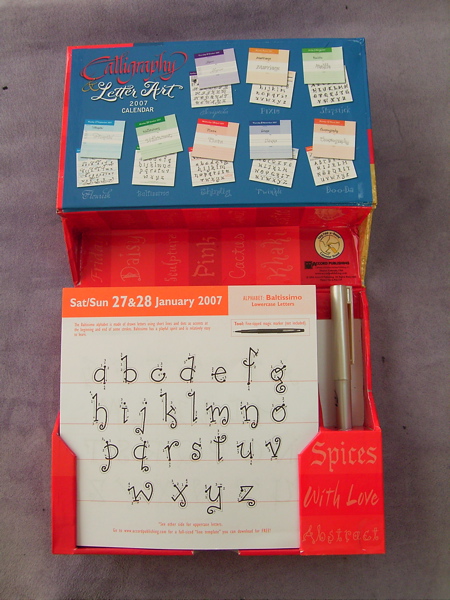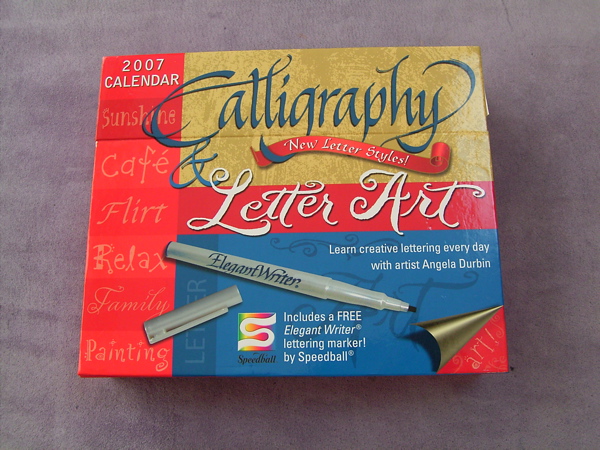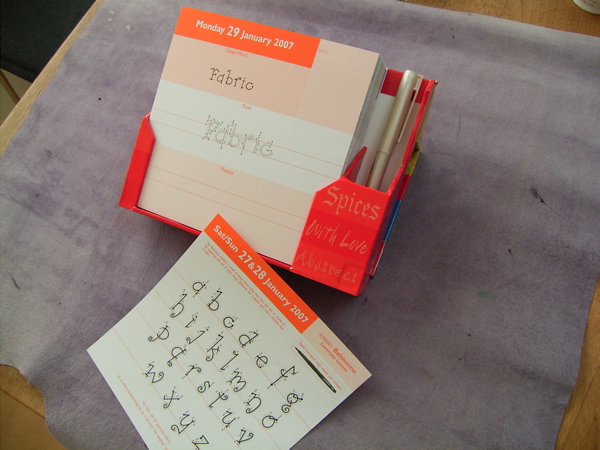
カリグラフィー練習カレンダー
クラスのmasayoさんがカリグラフィーを練習出来るカレンダーを、わざわざ持って来て見せてくれました。
前にこれについてお話してくれた時には、なんとなくもっと簡単なものをイメージしていましたが、こんなに立派なものだとは!驚きました。
ご覧の通り、一日一枚のカレンダー。日めくりの様に、書体を練習する事ができるのです。まず最初に書体のa~zが紹介され、次の日から、単語で練習となります。
そして毎日練習!
masayoさんはちゃんと1月の分は練習してありましたよ、素晴らしい!
で、一緒に購入したのがこれ。
この5色で色を作るのかしら〜。難しそうだけど、気軽に楽しもうと思えば結構面白いかもしれませんね。
昔、Marsha Bradyというカルフォルニア在住のカリグラファーに習ったことがありますが、彼女は「上手になりたかったら、とにかく毎日少しで良いからペンを持って書く様に。一日に一回は机に向かうこと」とアドバイスしていました。
こういう楽しいものがあれば、一日一枚、自然と練習できるかな〜?
なんだか楽しい書体ですね〜。アマゾンのあのシステムのことは、「あのシステムのお陰で出会えた」 と思うようにしています…。
確かにこのカレンダーには、フォーマルな書体というよりは手書きの楽しい書体が多かったような気がします。(でもゴシック体もありました)365日練習は大変そうですが、その姿勢は見習わなくちゃ!